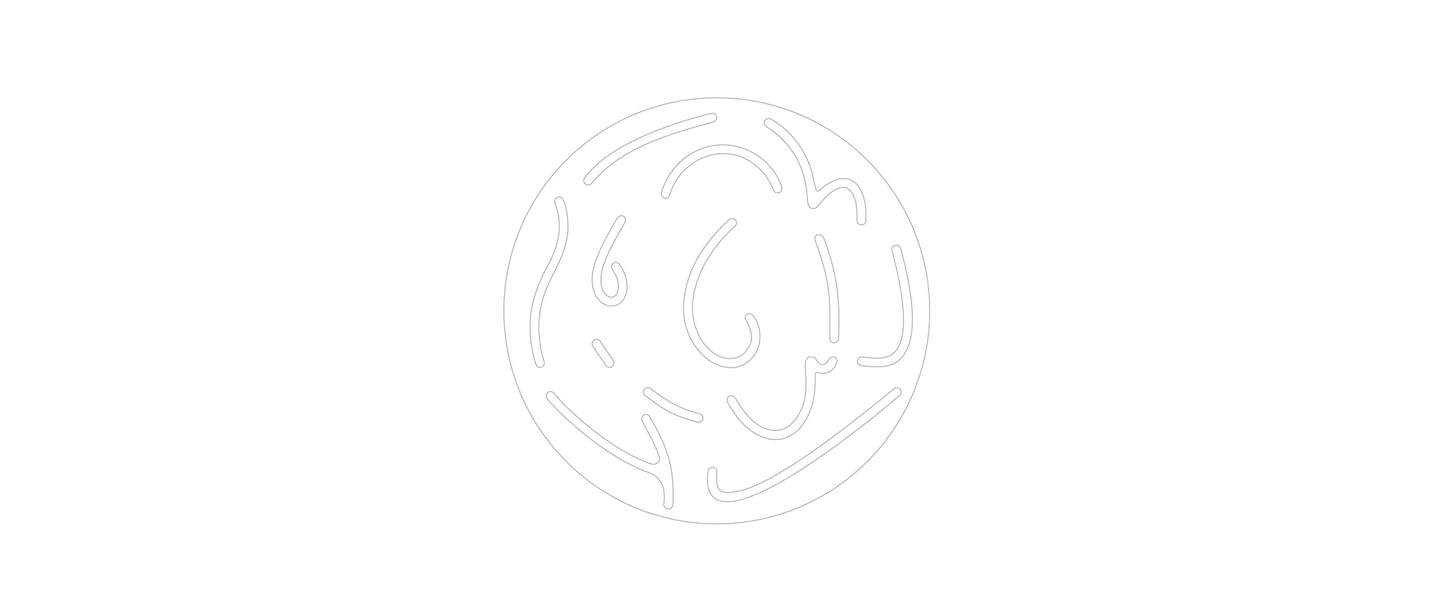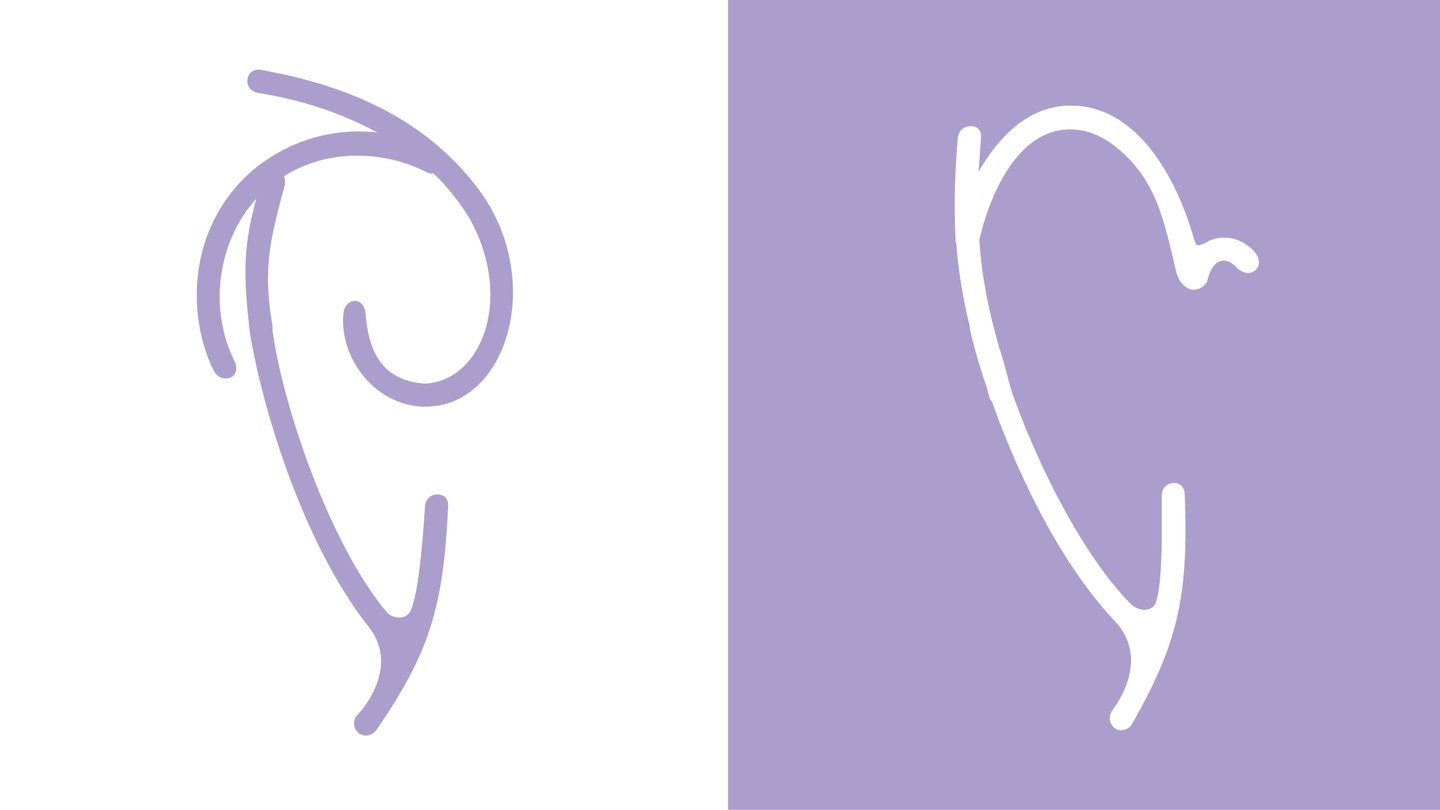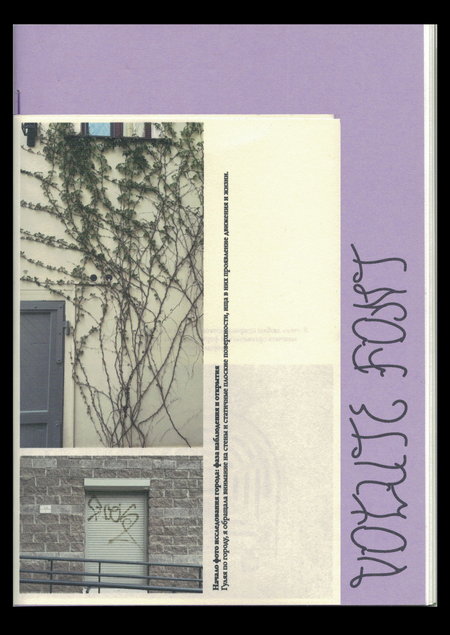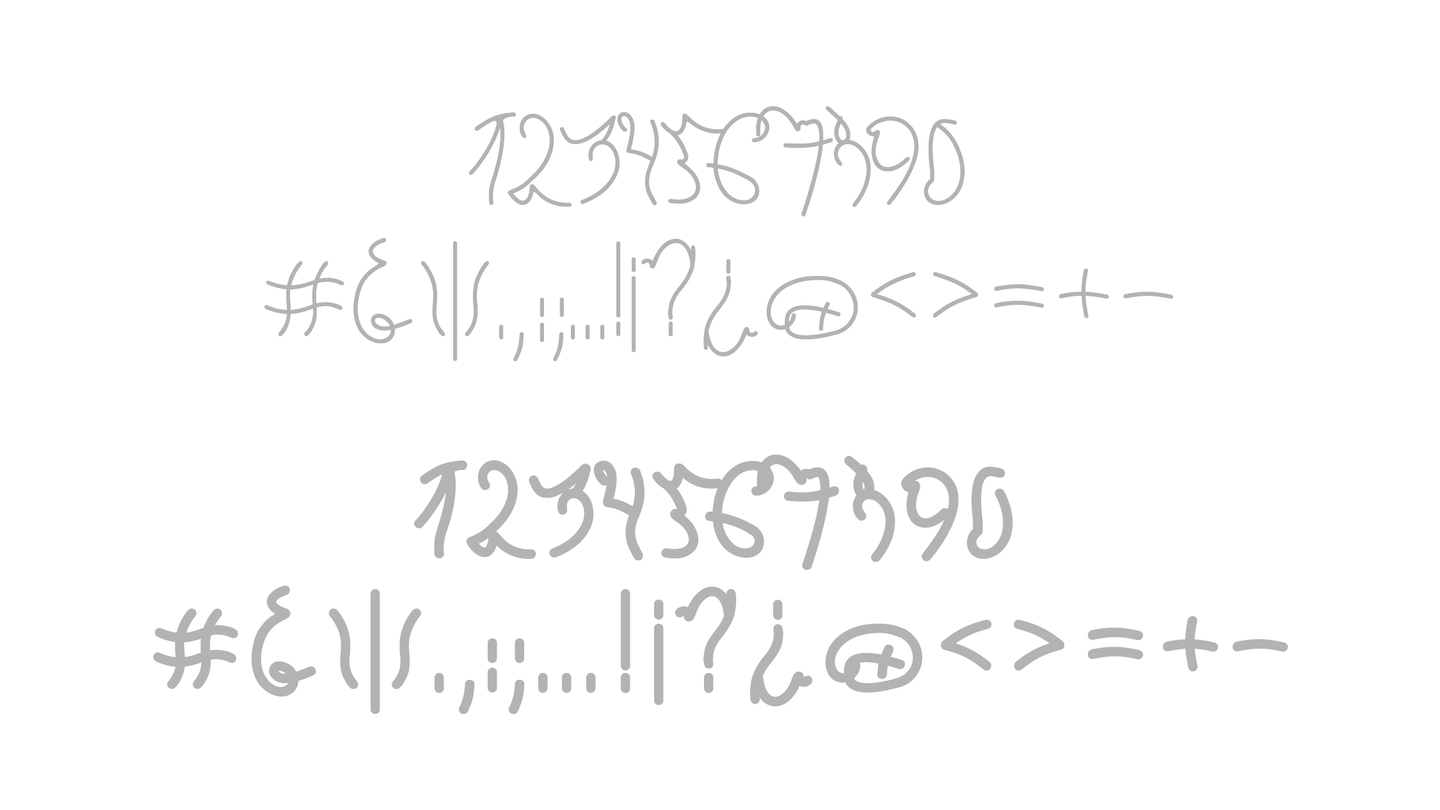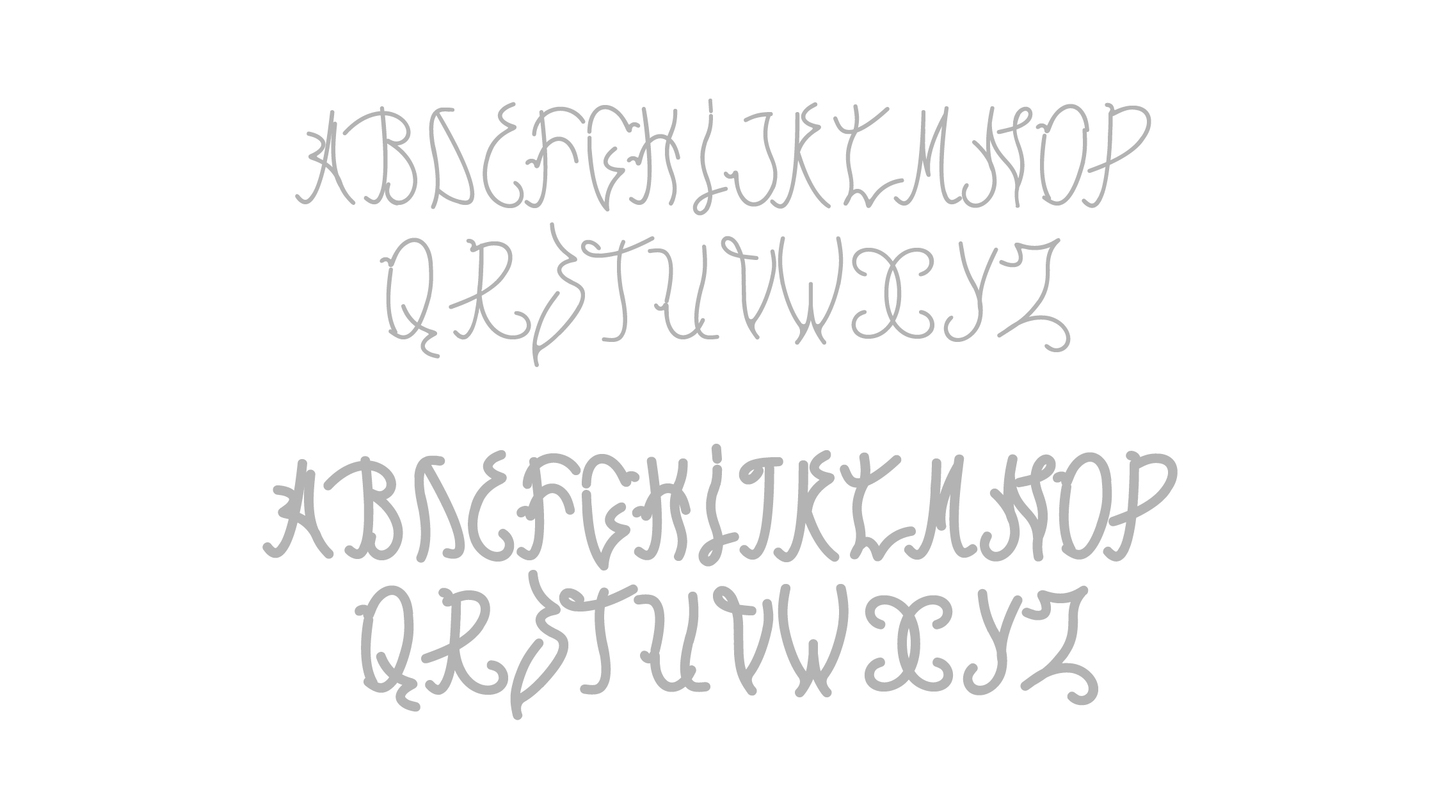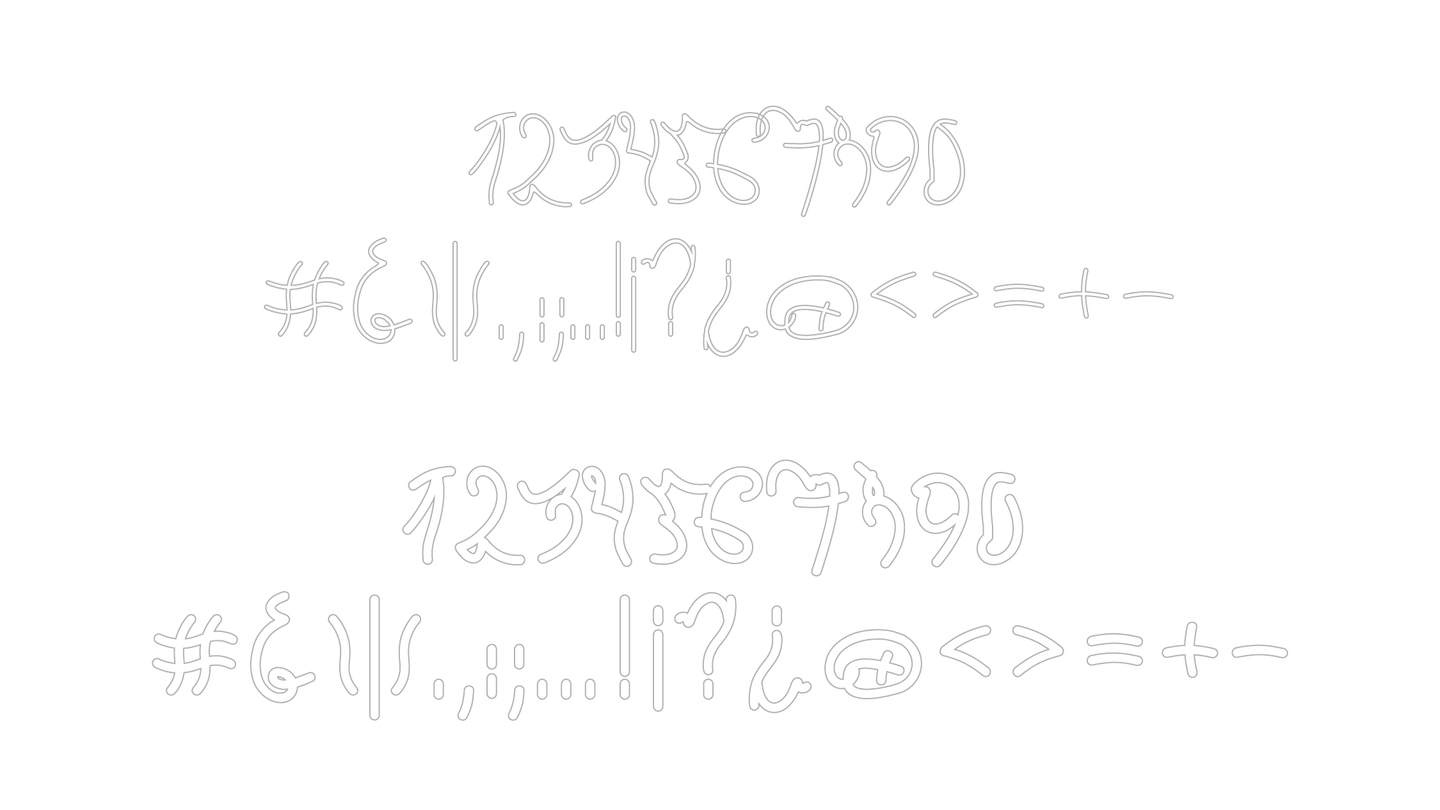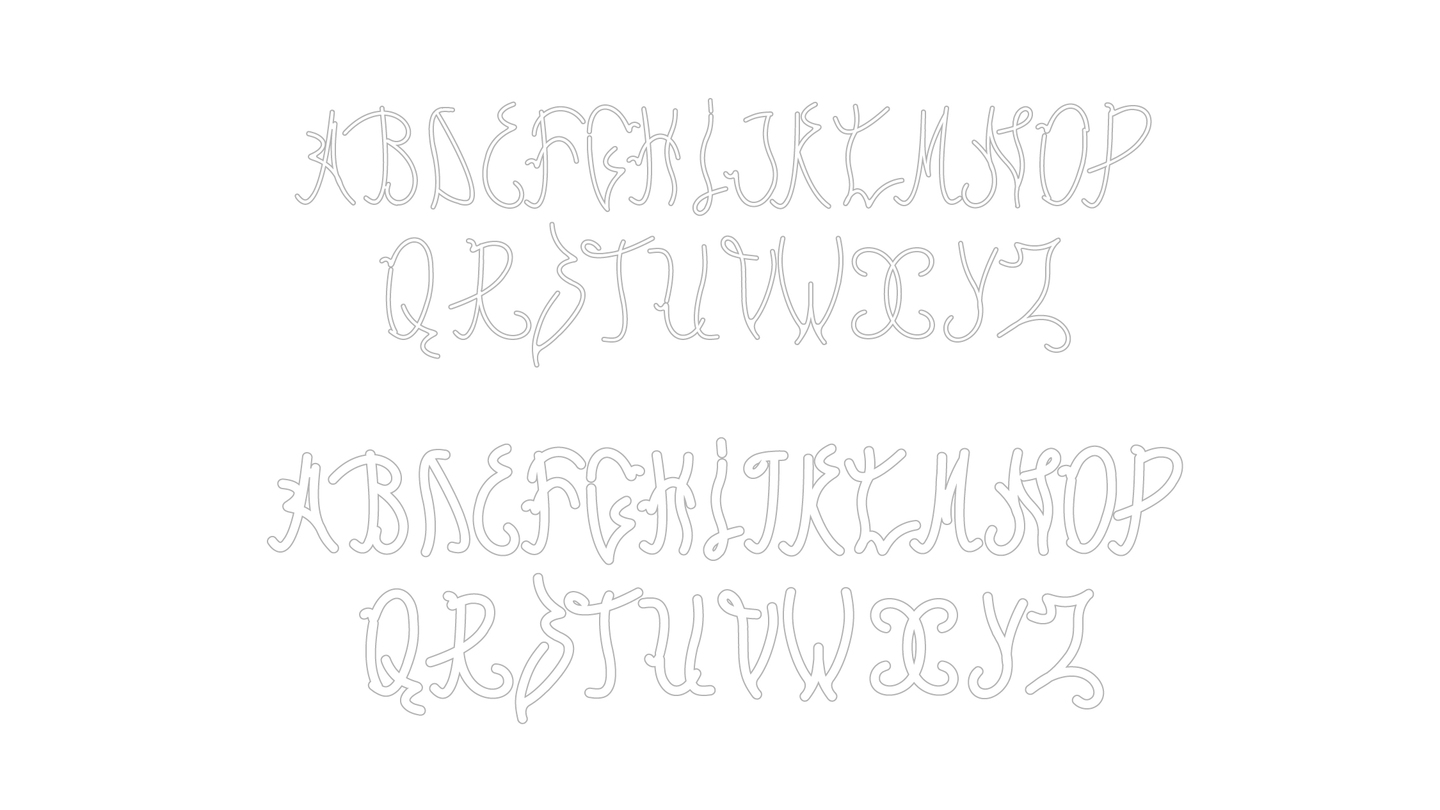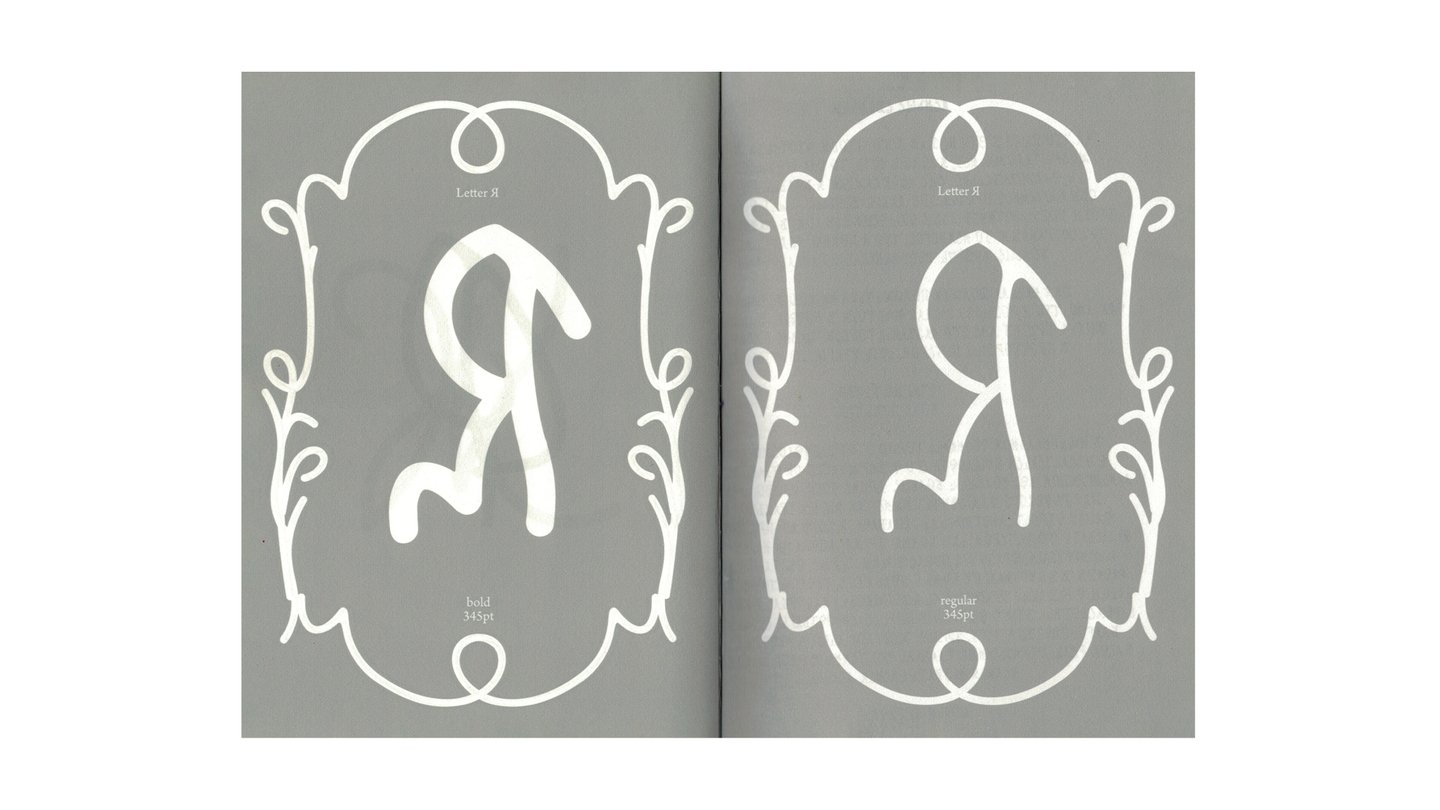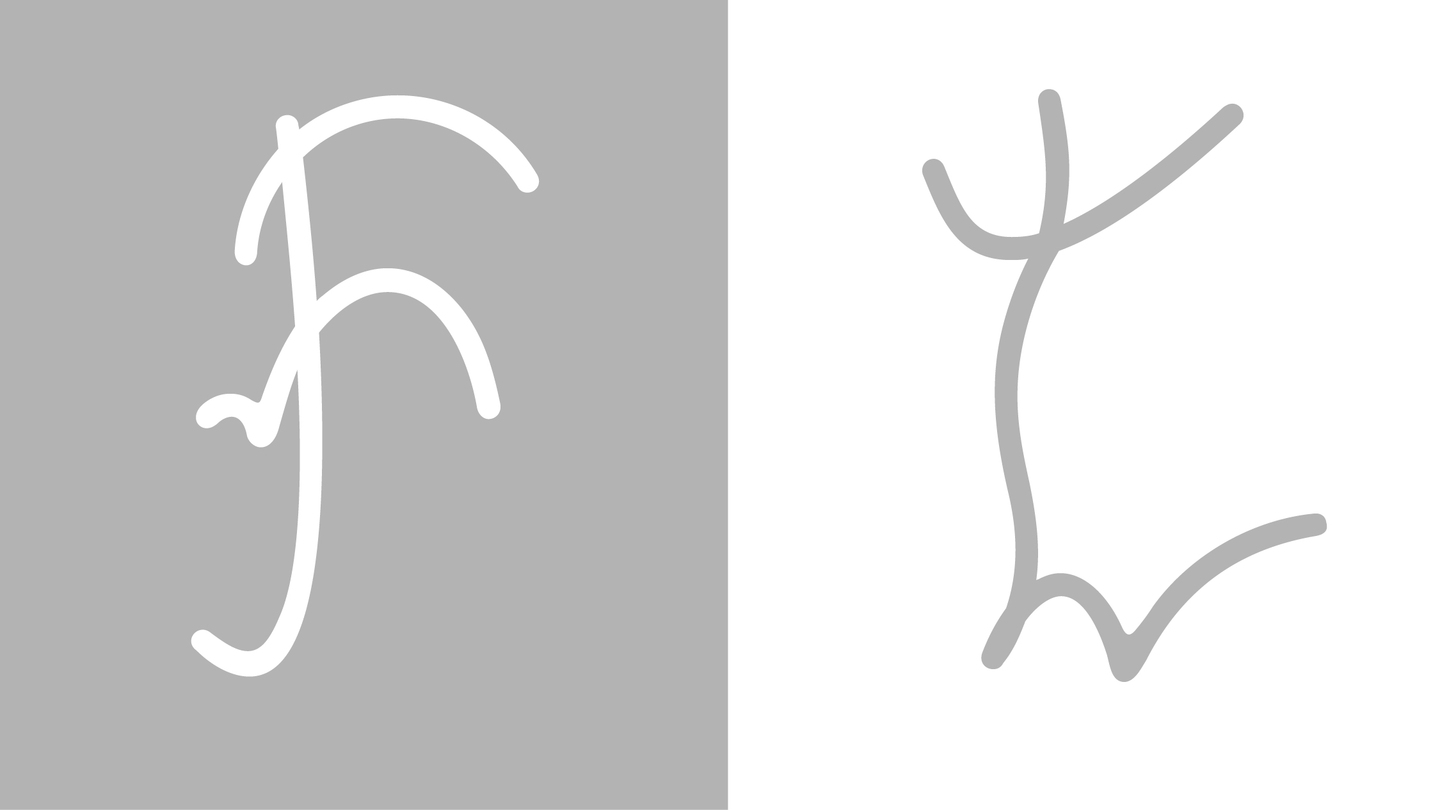
Volute (с французского — завиток, спираль, изогнутая линия) — акцидентный модульный шрифт, вдохновлённый органикой уличных надписей, напоминающих изгибы растений
Шрифт строится 13 модулей: извилистых, плавных и воздушных форм, которые вместе создают растительный мотив
Латиница
альтернативные варианты букв
Два начертания: regular и bold, а также версия outline
Кириллица
Зин
Структура зина поделена на две части: 1 — Фото исследование города. Фаза наблюдения и открытия 2 — Specimen. Буквы и модули